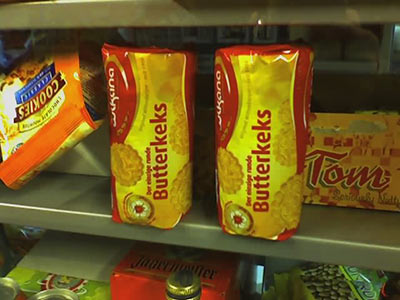
Entwickelt sich die FF Dax zur "neuen Rotis"?
Man sieht die Dax bei Transportunternehmen, auf Fertiggerichten u.v.m.
Wir die nächste Schrift "verheizt"?
Auf Fontwerk gibt es gerade die gleiche Diskussion/Feststellung. Wegen mir kann die DAX »verheizt« werden, ihre Überpräsenz nervt mich persönlich. Ich mag sie als Schrift als solche aber eh nicht.
Aber gut zu wissen, dass die "Dax-Flut" nicht nur mir auffällt.
Gerade war ich Portugal unterwegs und bin echt überrascht gewesen: Jedes dritte Unternehmen nimmt die Dax, die ganze Gegend war voll davon. Es lohnt sich also, die Palette mit zu digitalisieren :-)
Man sieht die Dax bei Transportunternehmen, auf Fertiggerichten u.v.m.
Wir die nächste Schrift "verheizt"?
Oh ja, wenn man erstmal darauf achtet ... heute allein 4 Sichtungen, zwei davon hab ich mit dem Handy geknipst.
Die anderen waren ein Kalender bei der Post und das omnipräsente Norwegen-Poster mit dieser merkwürdigen Schriftmischung.